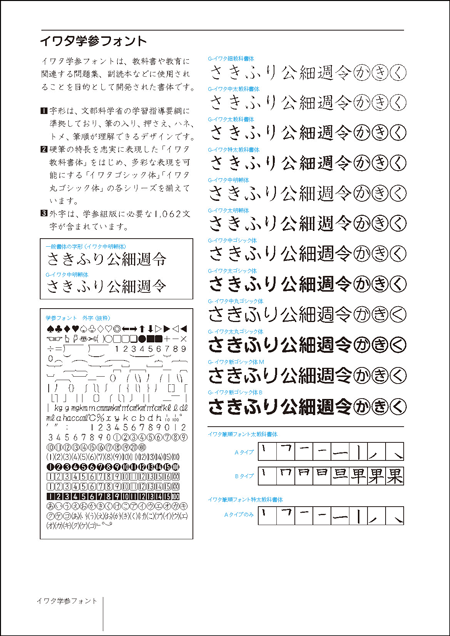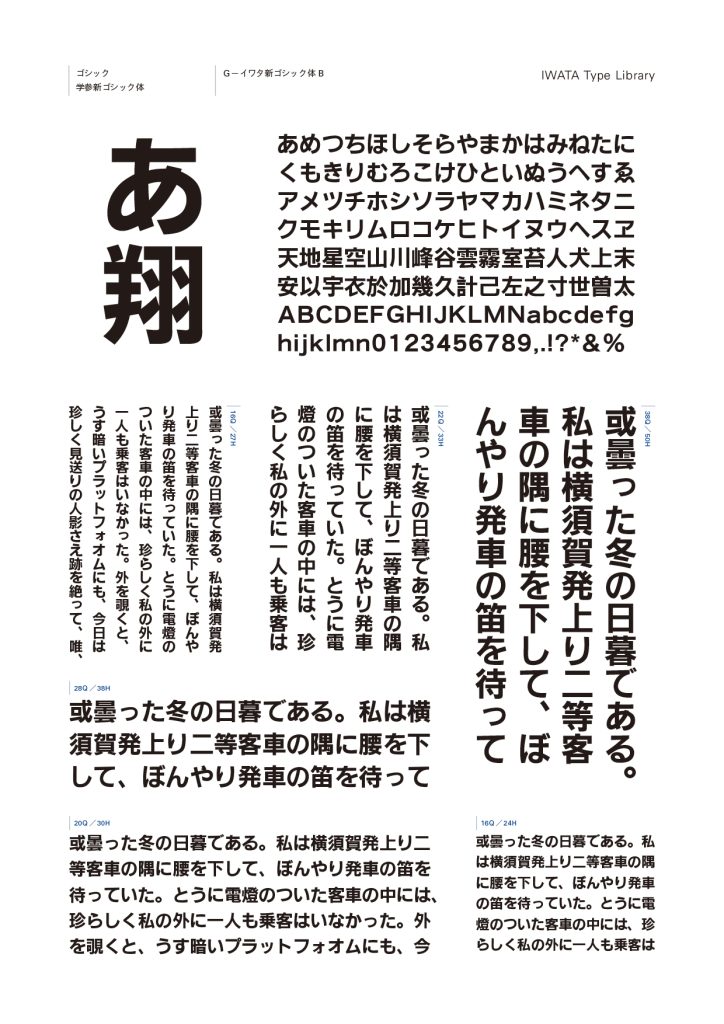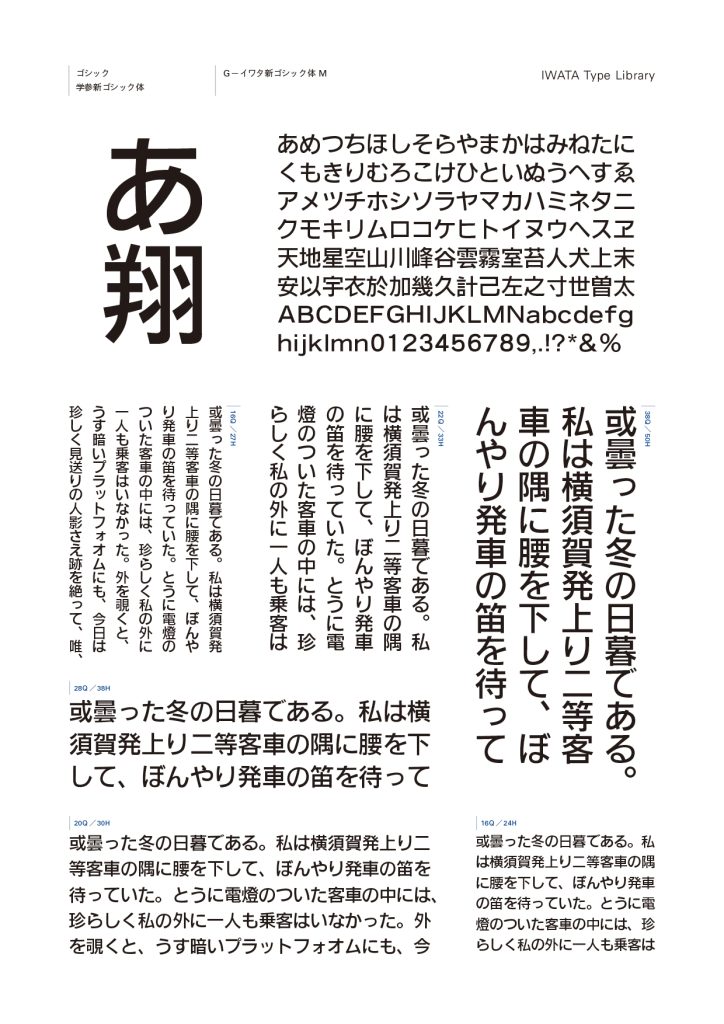
教科書等の教育に関する著作物、あるいは教育現場にて制作される問題集、副読本等の制作に使用されることを目的にとして開発されました。
教育漢字1,006文字についてハネ・トメ・押さえ・筆順等を文部科学省の学習指導要領の字形に準拠して制作されたフォントです。小学校の教科書・ドリル・学習参考書に最適です。プロフェッショナルな学習組版に必要な外字1,036文字も付いています。